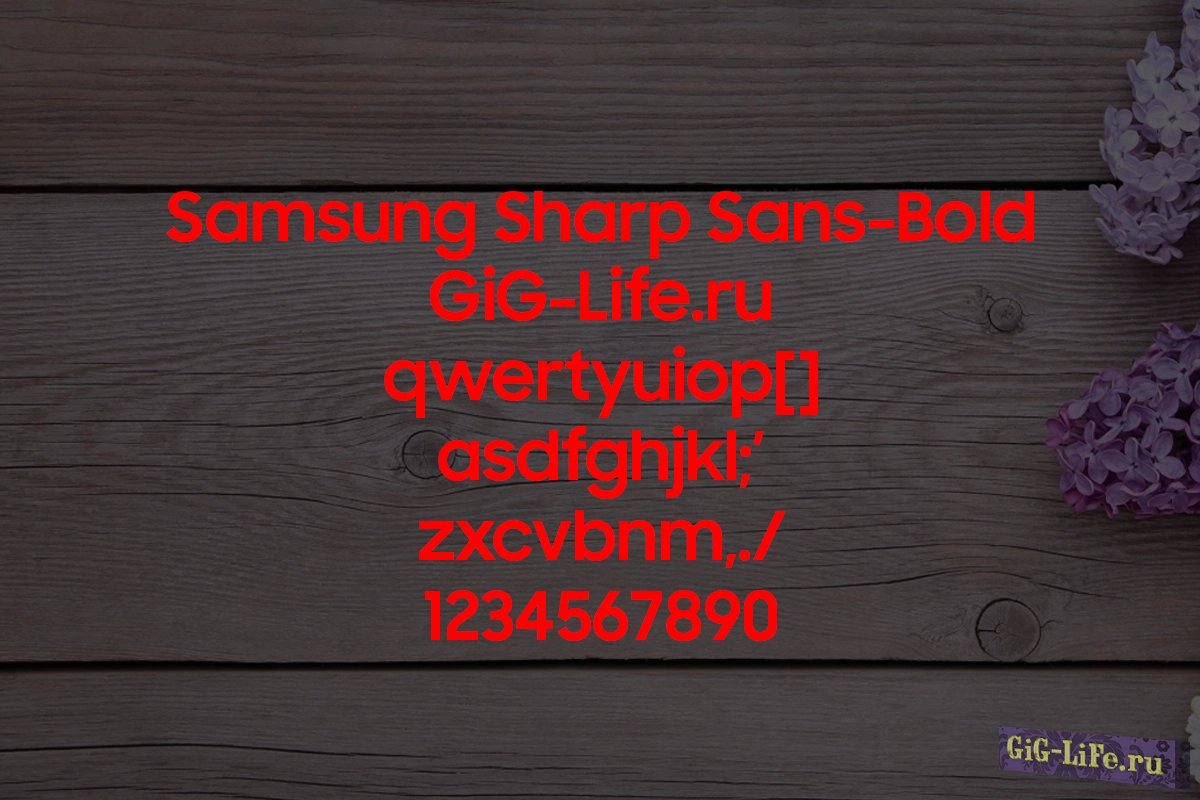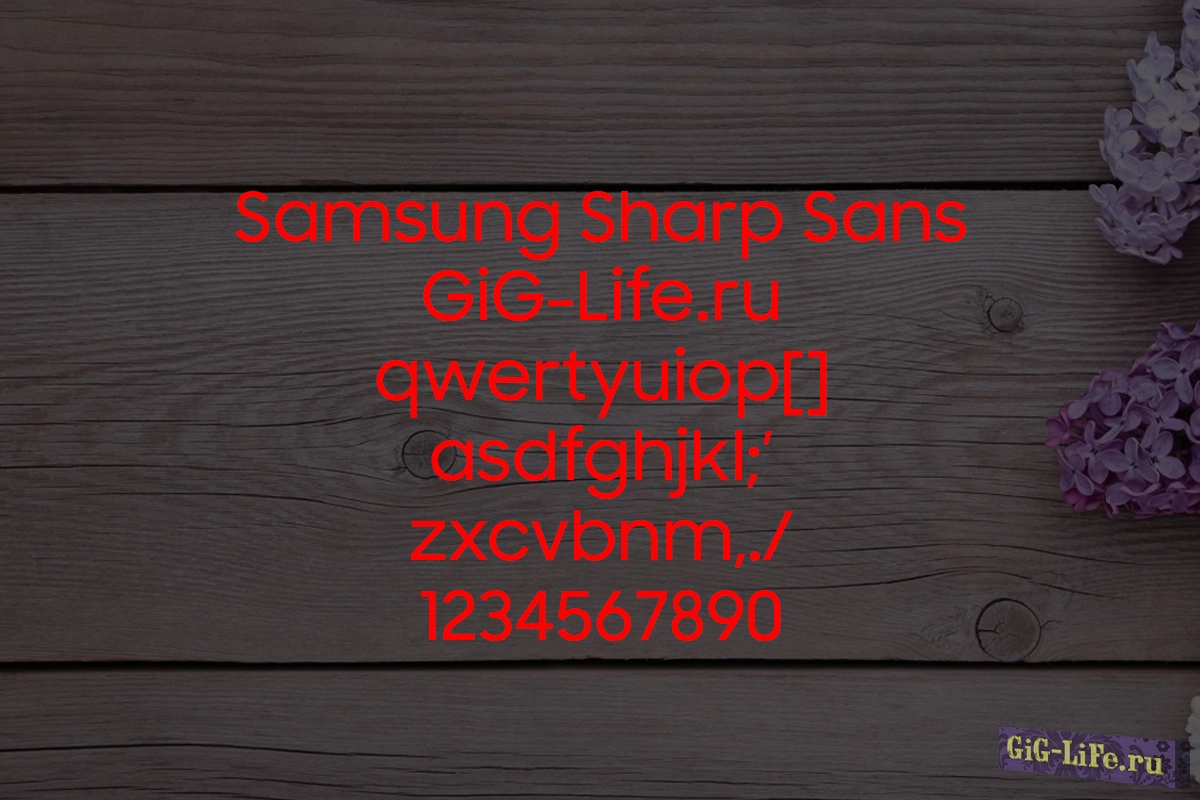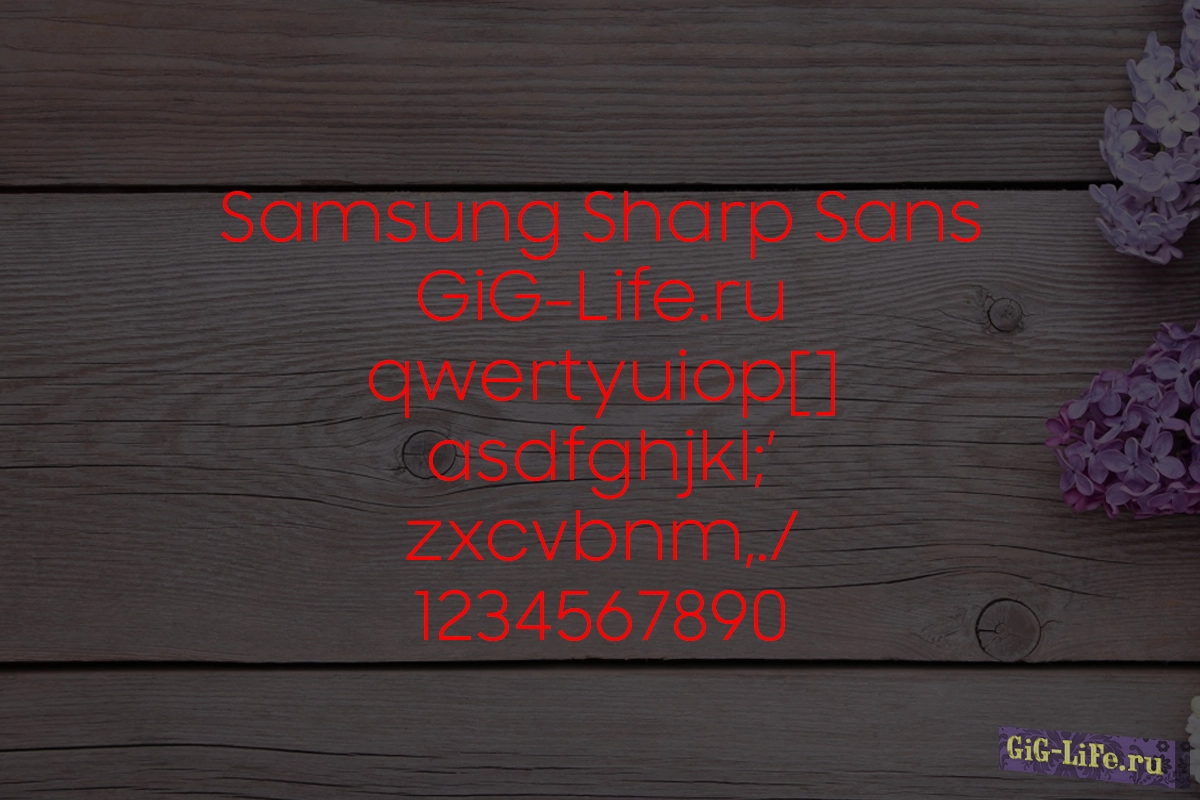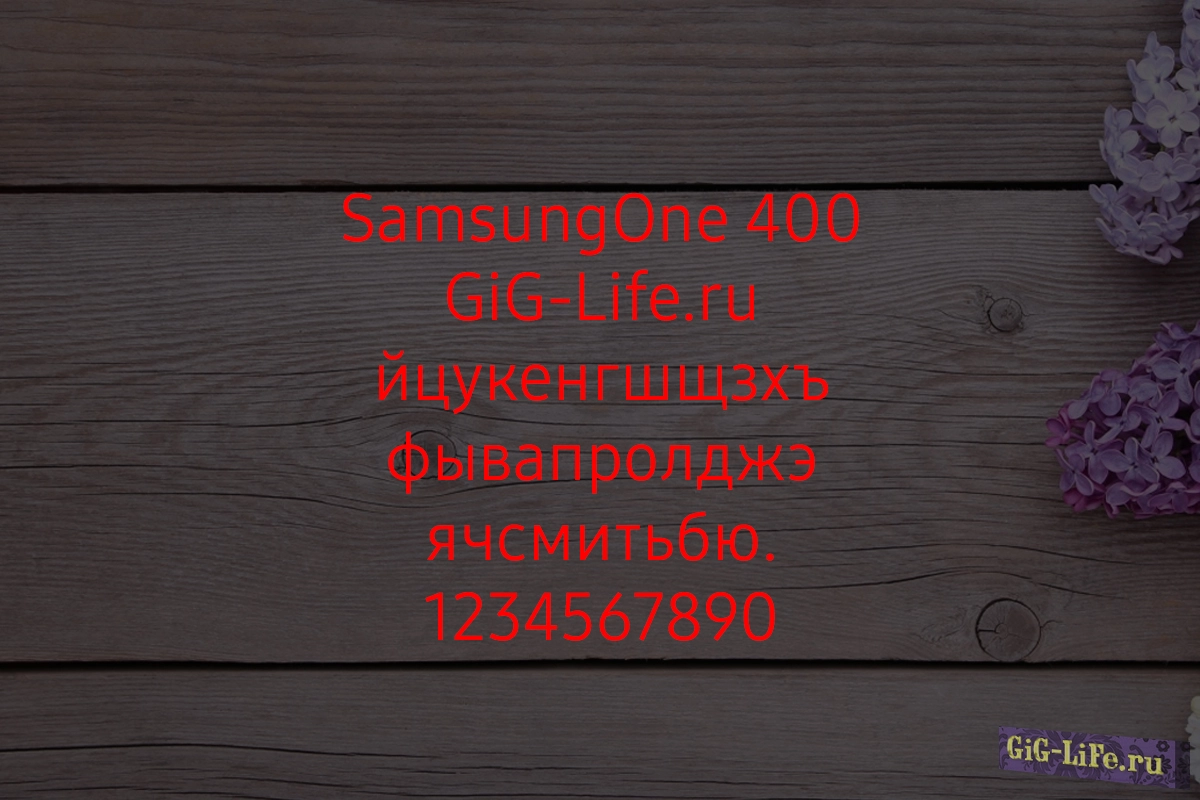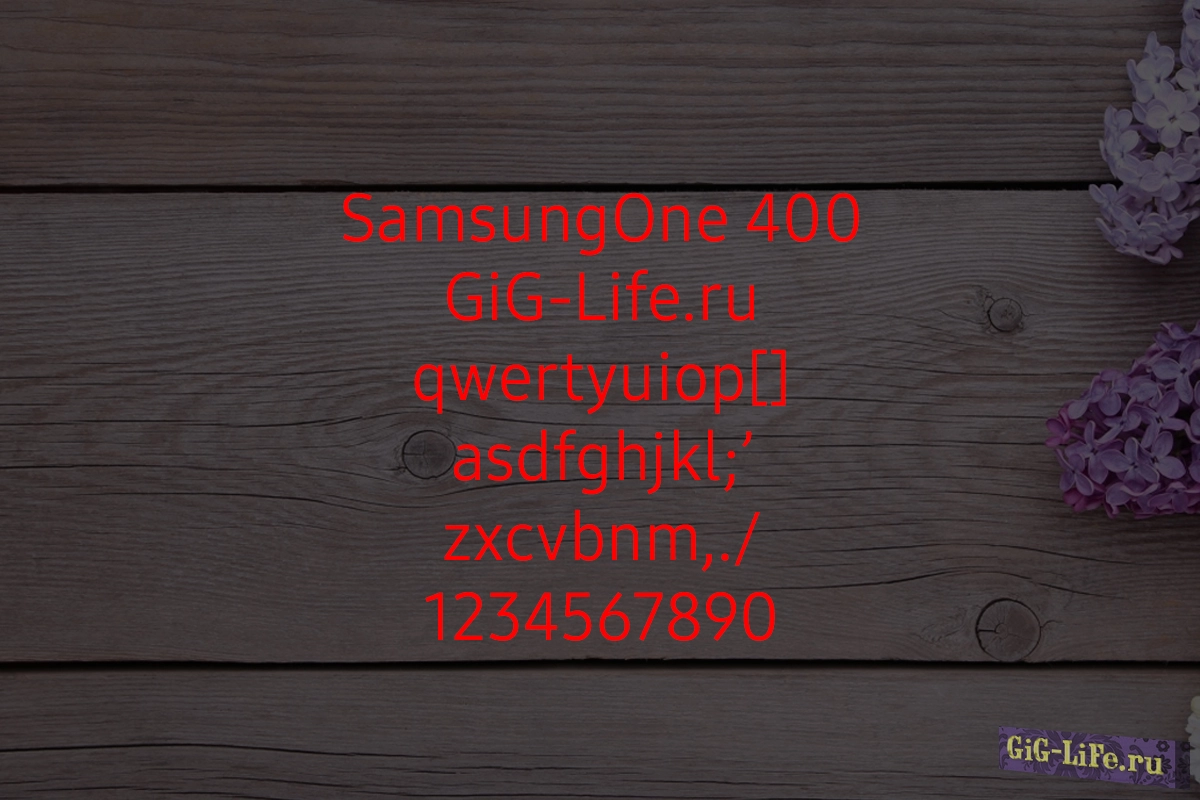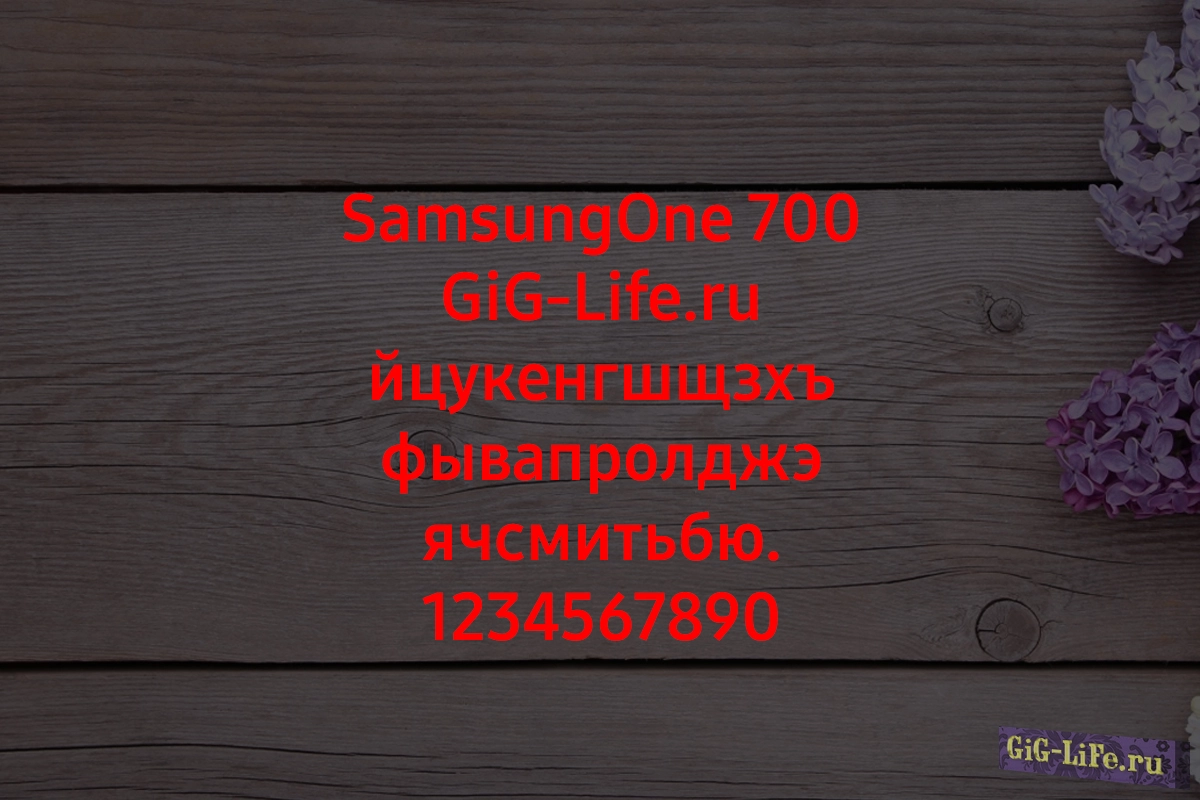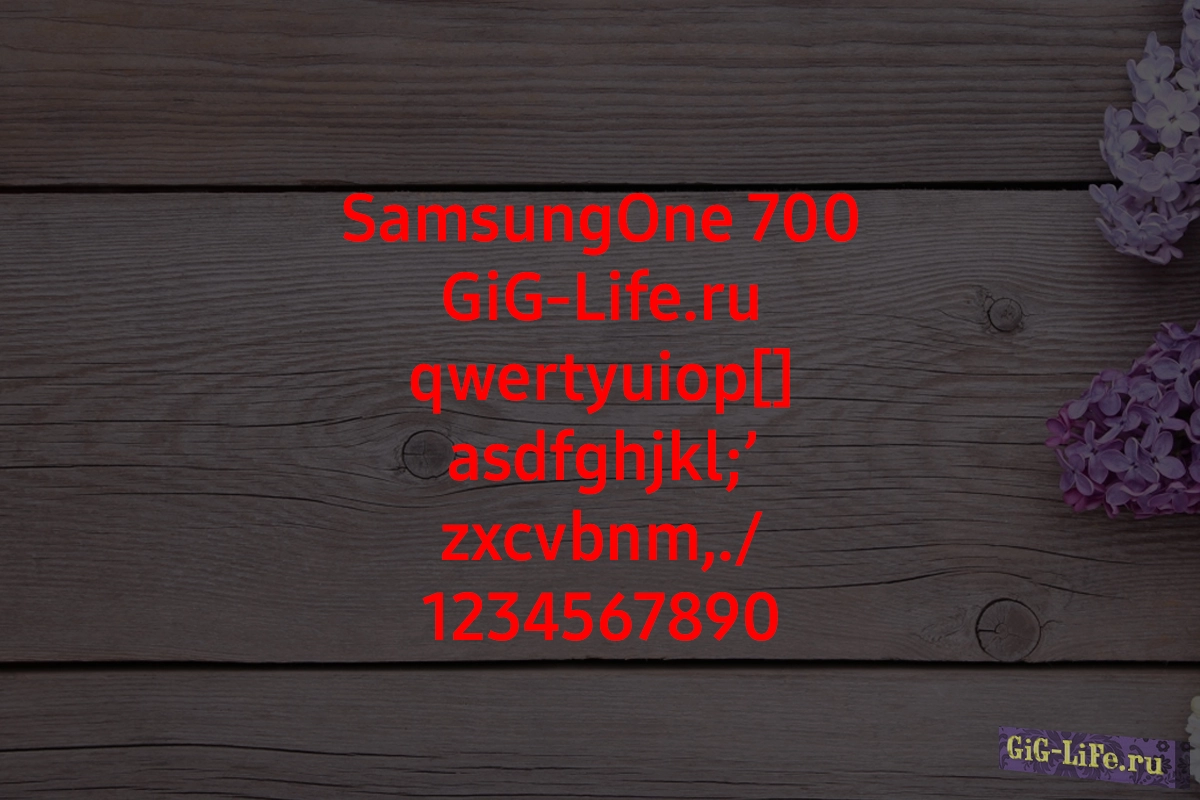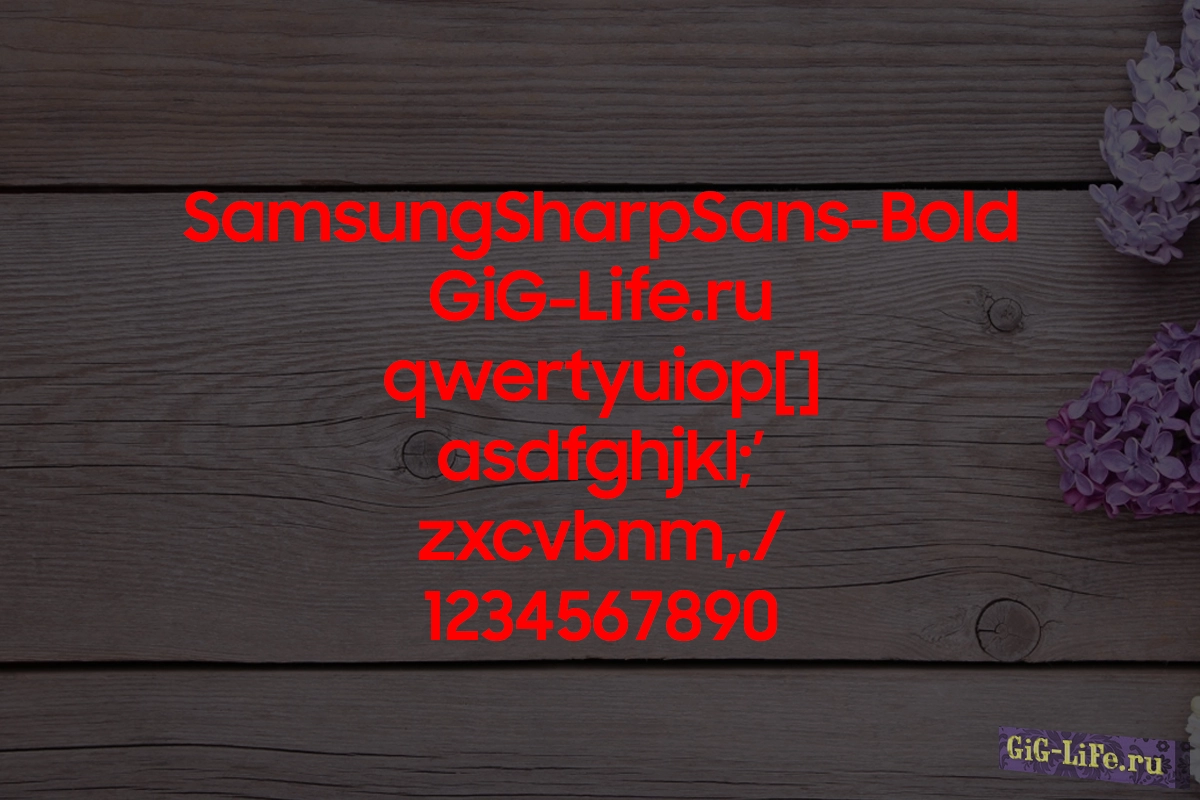
Samsung Typeface Collection: Шрифты премиум-класса для современного дизайна
Откройте для себя элегантную коллекцию фирменных шрифтов Samsung, разработанных для создания профессиональных проектов любой сложности. В набор входят два уникальных семейства шрифтов, которые станут идеальным выбором для вашего следующего проекта.
SamsungOne - универсальное семейство шрифтов с двумя весовыми вариантами:
• SamsungOne 400 - регулярный вес для основного текста
• SamsungOne 700 - полужирное начертание для заголовков и акцентов
SamsungSharpSans - динамичное семейство с четкими геометрическими формами:
• SamsungSharpSans-Bold - выразительное жирное начертание
• SamsungSharpSans-Medium - средний вес для комфортного чтения
• SamsungSharpSans - базовое начертание
Идеально подходят для:
• Корпоративной документации
• Веб-дизайна
• Брендинга
• Рекламных материалов
• Изменения текста в смс
• UI/UX дизайна
Создайте современный и профессиональный облик ваших проектов с помощью этих стильных и функциональных шрифтов от ведущего технологического бренда.